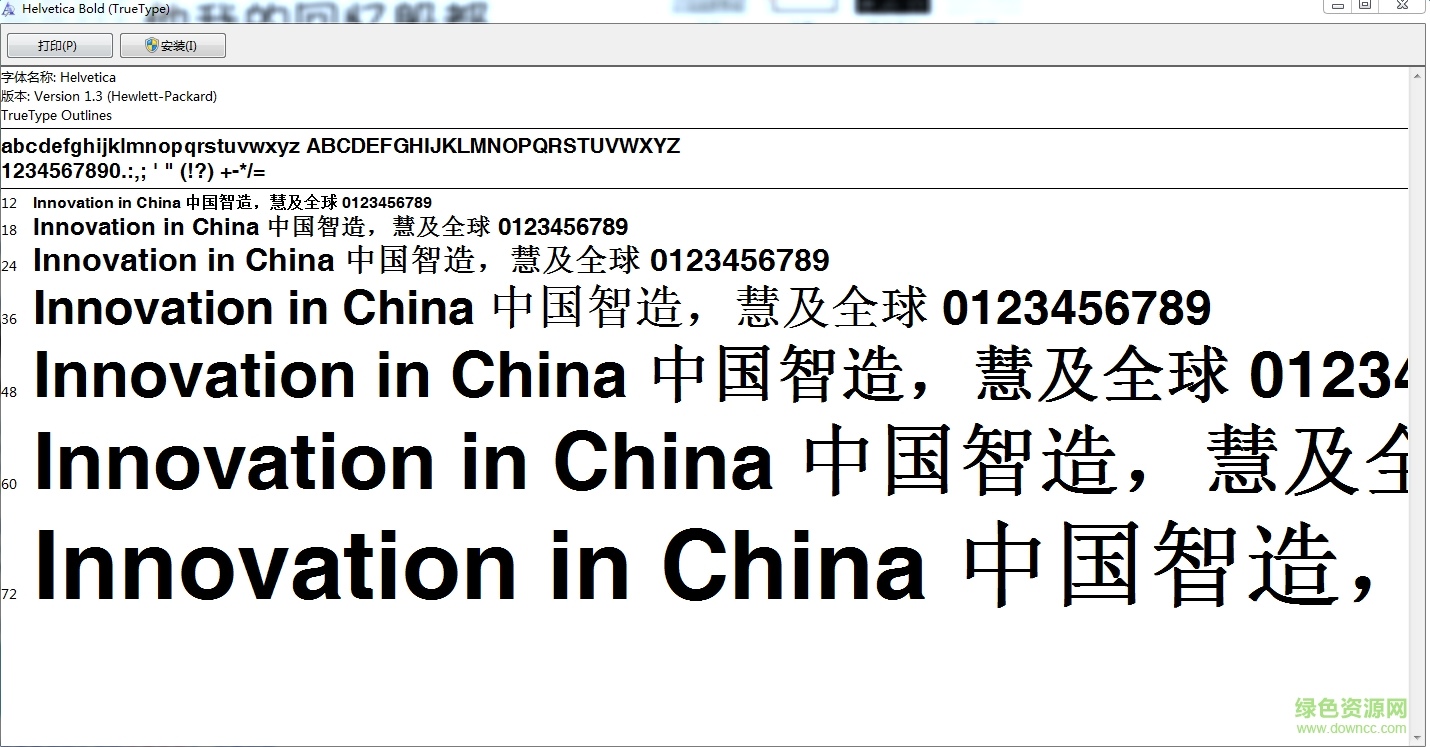
helvetica bold是什么字體?helvetica bold字體是一款十分工整的英文字體,粗細勻稱,間距得當(dāng),常用于ps中,有需要者歡迎在綠色資源網(wǎng)下載!
helvetica bold字體簡單端秀,整體效果十分突出,適用于平面設(shè)計、廣告宣傳、影視設(shè)計等各個方面~!